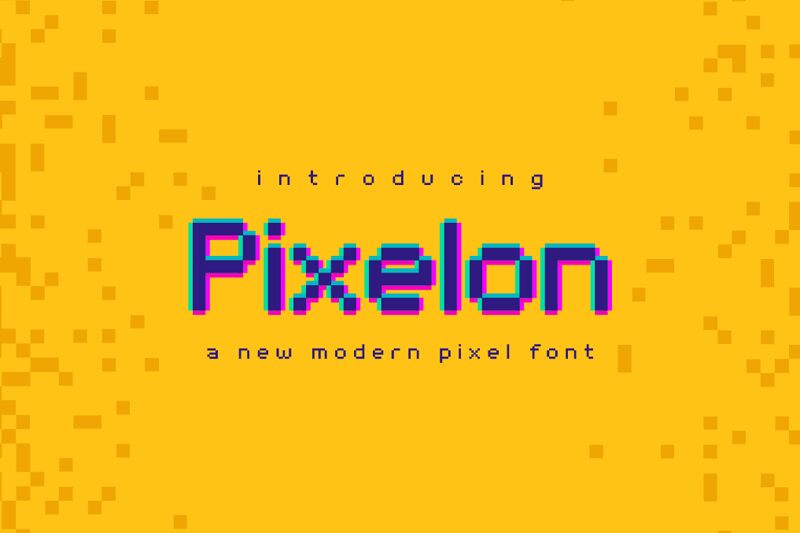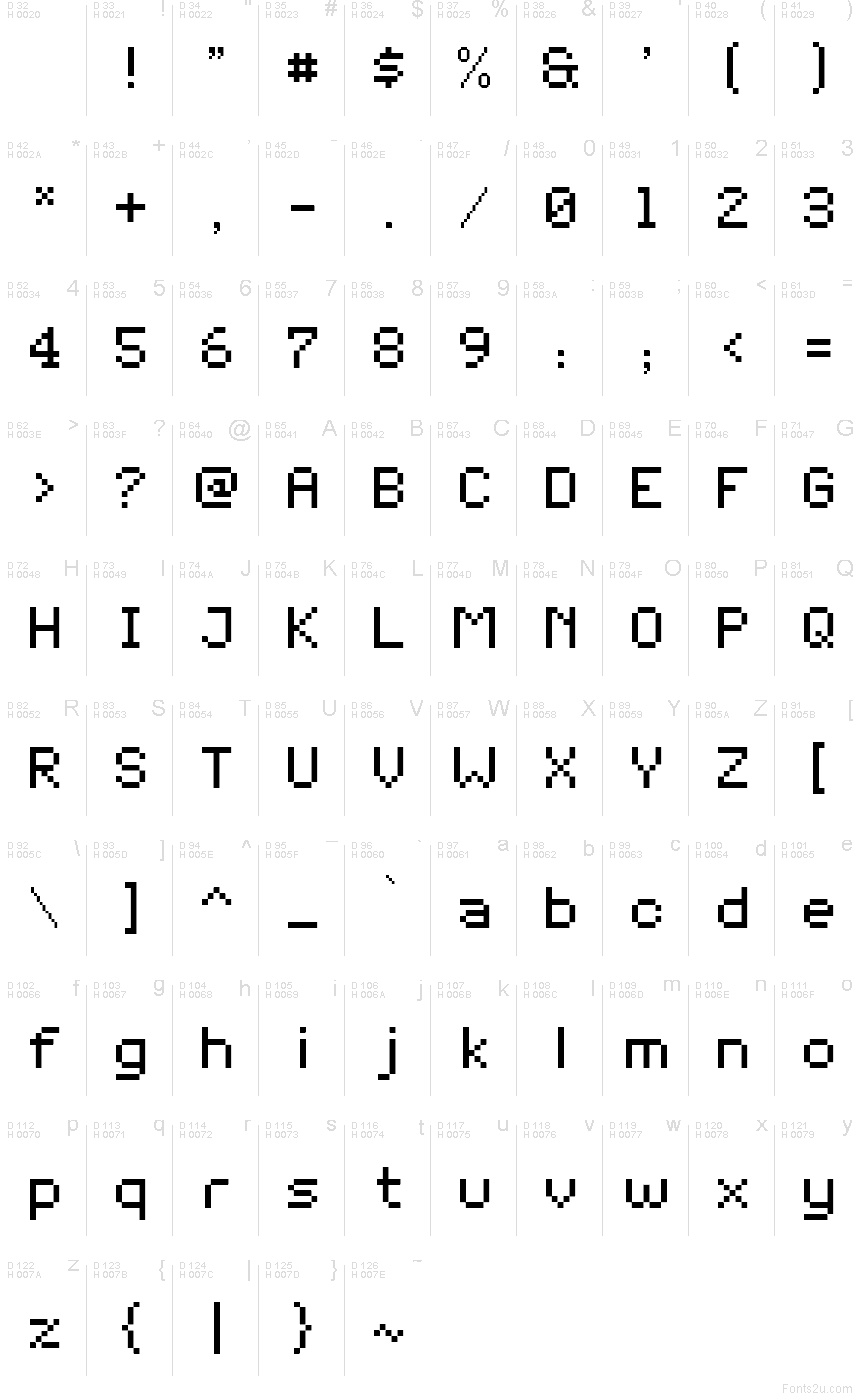
Pixelon, da Studio AKTYPE, é uma fonte pixel bitmap gratuita com aquele visual robusto dos monitores antigos. As letras são construídas a partir de blocos quadrados e diagonais escalonadas, conferindo-lhe o ritmo direto dos menus de jogos, títulos de softwares antigos e interfaces da era dos portáteis, longe da suavidade das fontes pixel modernas.
Esta fonte gratuita encaixa-se perfeitamente em branding de jogos retrô, flyers de arcade, telas de abertura de aplicativos, títulos de cartazes e gráficos para streaming que pedem aquele impacto digital. Também funciona bem para títulos curtos e logotipos, pois as junções em bloco e as curvas simplificadas mantêm as letras marcantes e inconfundivelmente enraizadas na cultura bitmap.